Hacía un tiempo desde que no compartía algo en esta gran sección que es RADAR y hoy, le toca el espacio a un proyecto tipográfico increíble que he vendio siguiendo desde hace un tiempo y que considero merece toda la atención, sobre todo si somos de esos diseñadores que nunca encuentra la tipografía perfecta para un proyecto.
A principios de 2021 Indian Type Foundry (ITF) hizo algo que pocas fundiciones tipográficas se atreven a hacer y eso fue lanzar gratuitamente el 25% de su catálogo de tipografías. Bueno, hicieron más que eso, porque no siendo suficiente, lo hicieron a través de su propio servicio de distribución gratuita llamado Fontshare.
Nuestra misión es garantizar que todos tengan la oportunidad de usar hermosas fuentes en sus diseños de forma gratuita — ITF.
En el anuncio, ITF mencionó que durante años ellos han ofrecido a estudiantes, instituciones de diseño y otras organizaciones sin fines de lucro todas sus fuentes comerciales de forma gratuita y, que siguiendo esa línea con el objetivo de ir aún más allá y ayudar a marcas y diseñadores que, sin presupuesto, desean acceder a una tipografía atractiva y de alta calidad.
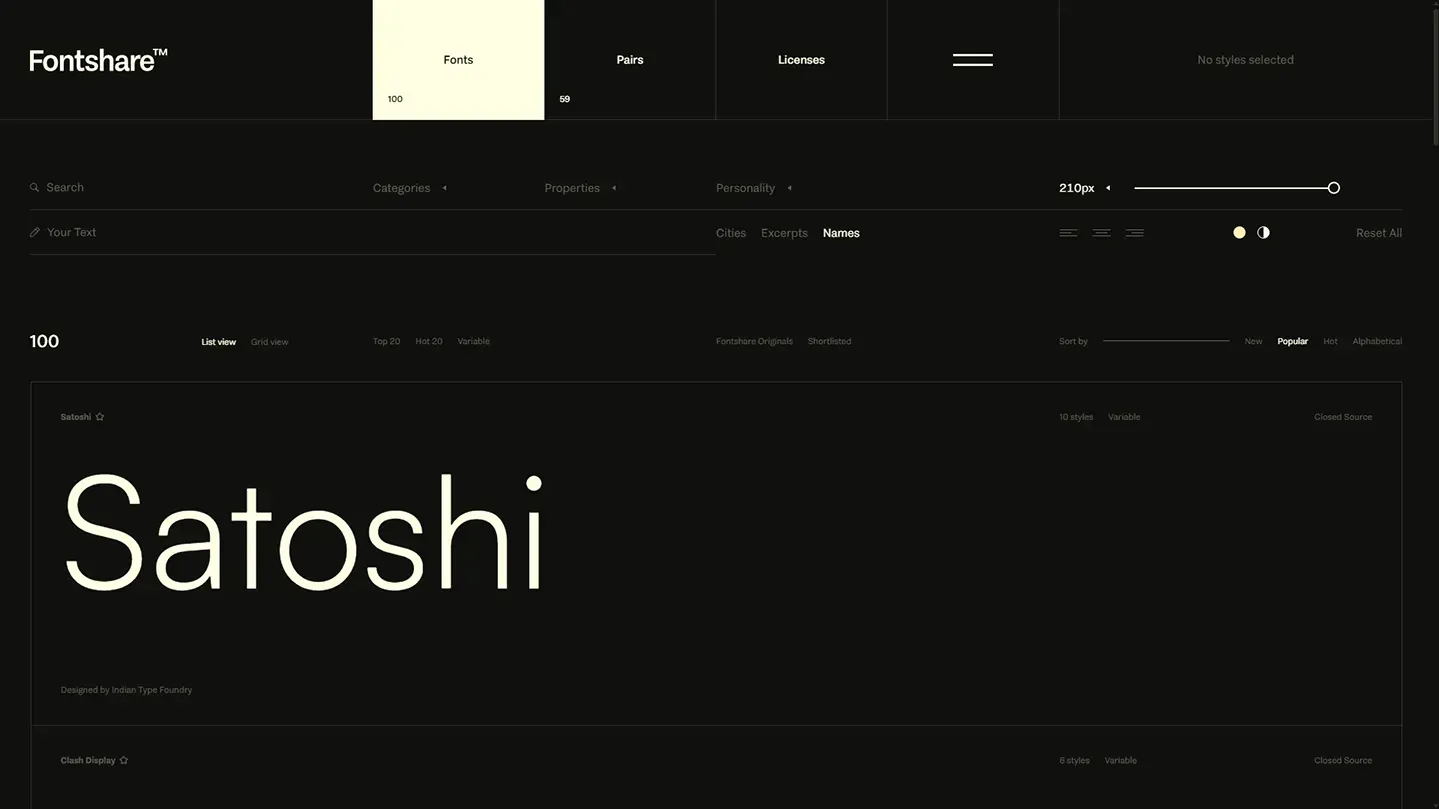
Lo que a mi criterio es una de las características más increíbles de este proyecto es que la conceción de las tipografías en Fontshare es tanto para un uso personal así como comercial. Como mencioné en el párrafo anterior, además de esas conceciones, ITF también ha invertido durante años recursos para el desarrollo de fuentes para idomas poco comunes o que se encuentran en peligro de extinción. Fontshare como proyecto habla mucho del compromiso con la filosofía que impulsa a la fundición más allá de lo que el negocio representa.
Algo que hace diferente a este proyecto de otras ofertas como podría ser Google Fonts, donde si bien tienen un catálogo inmenso, se siente opacado por la cantidad de opciones que en la práctica no se sienten «premium», las tipografías ofrecidas en Fontshare son tipografías premium en toda la extensión de la palabra, no una versión reducida o limitada de la premium completa.
El servicio fue lanzado en 2021 con 50 tipografías del catálogo de ITF y a día de hoy (agosto 2025) hay disponible 100 tipografías en su catálogo de forma gratuita. El proyecto es completamente sostenido por ITF sin solicitar, rastrear o almacenar datos personales del usuario lo que en los tiempos que vivimos parece de cuento. Sin duda es un proyecto increíble.